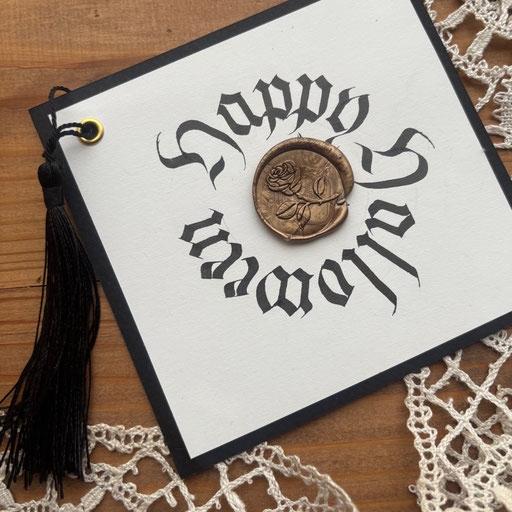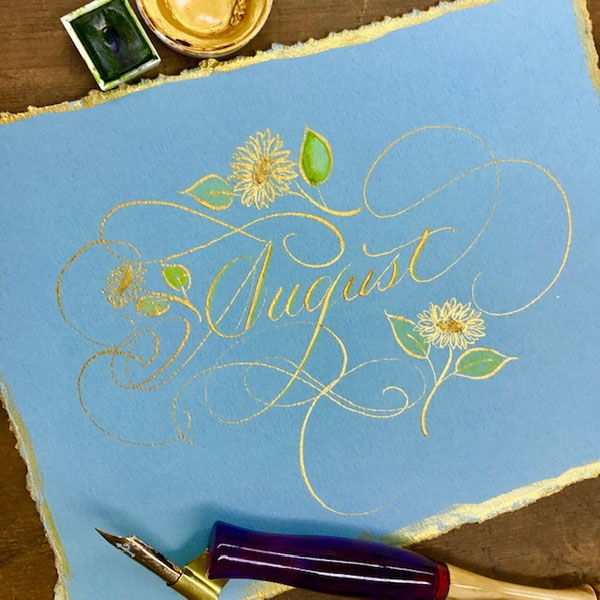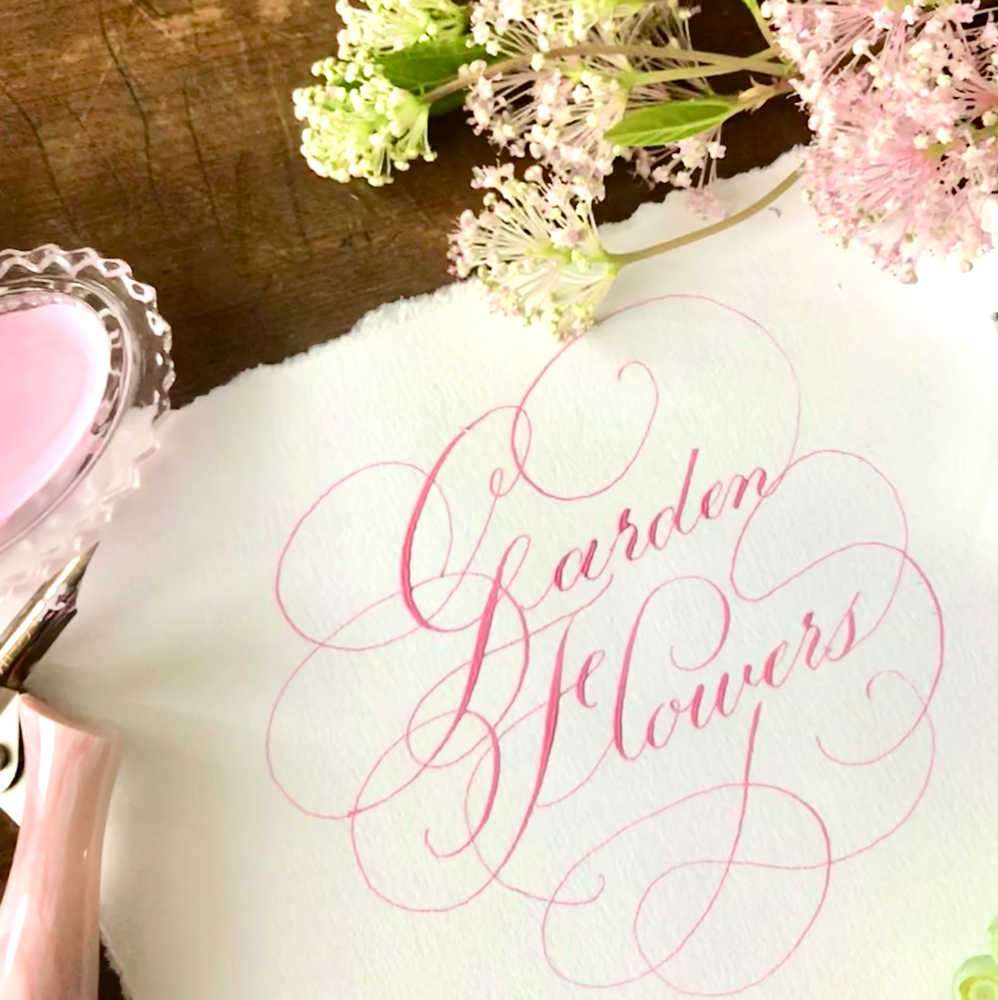
定員5名様までの少人数で、西洋伝統のカリグラフィーをクラシカルからモダンな表現まで勉強していただけます。講師資格も取得できます。
カリグラフィー専用ペンで文字を書く時、ペンから手に伝わる感覚はとてもここち良く、楽器の演奏をしているようです。
あわただしい日常の中、集中して文字を書くだけでリラックスできます。
1996年よりカリグラフィーを学び、2000年より小田原真喜子先生のアシスタント講師を務めたのち、 NHK文化センター名古屋教室、NHK文化センター豊橋教室、ヴォーグ学園大阪校など愛知県を中心にカリグラフィーのレッスンを始めました。
カリグラフィーを通して多くの生徒様と出会い、同じ方向をみつめ、ご一緒の時間を持つことは私にとって大きな喜びです。